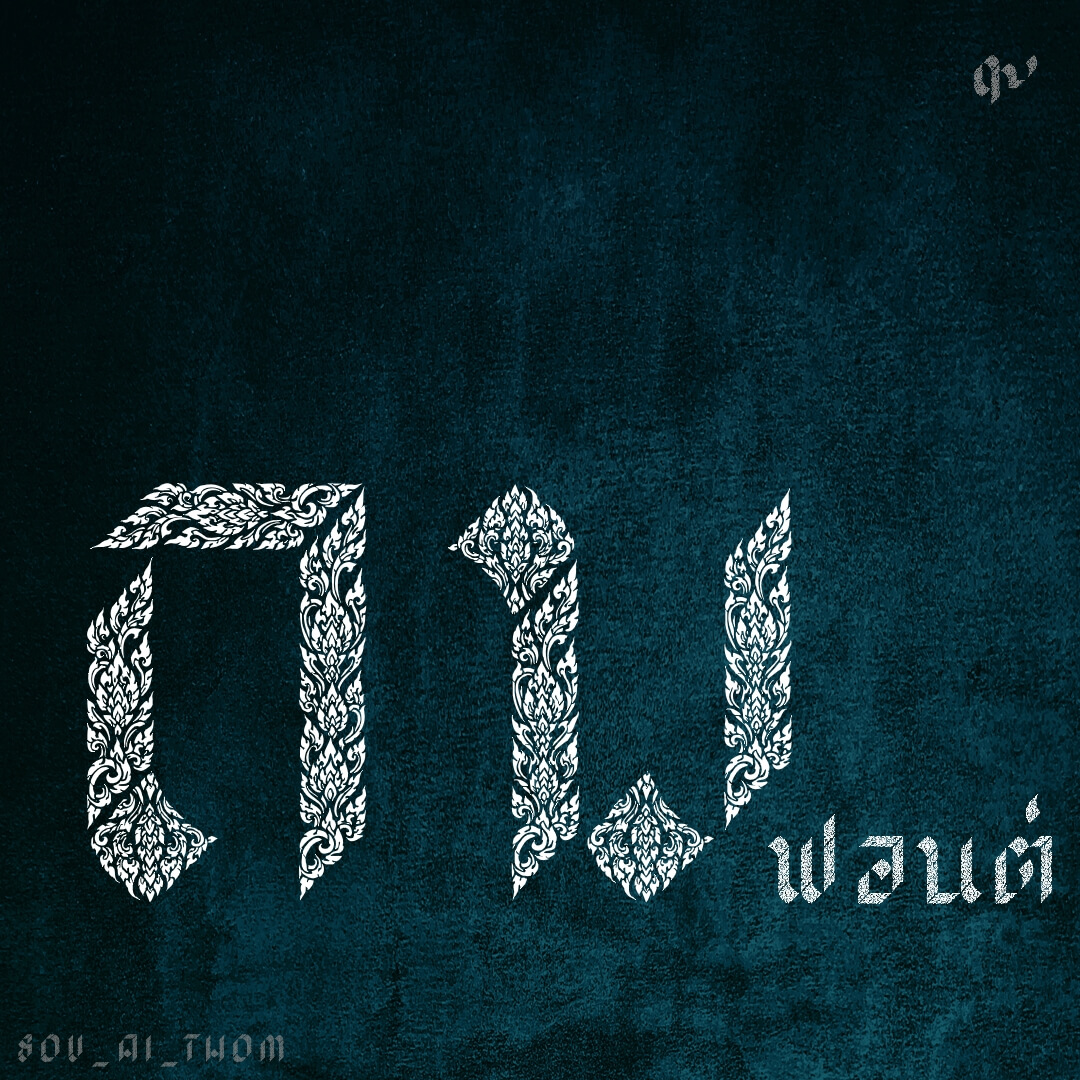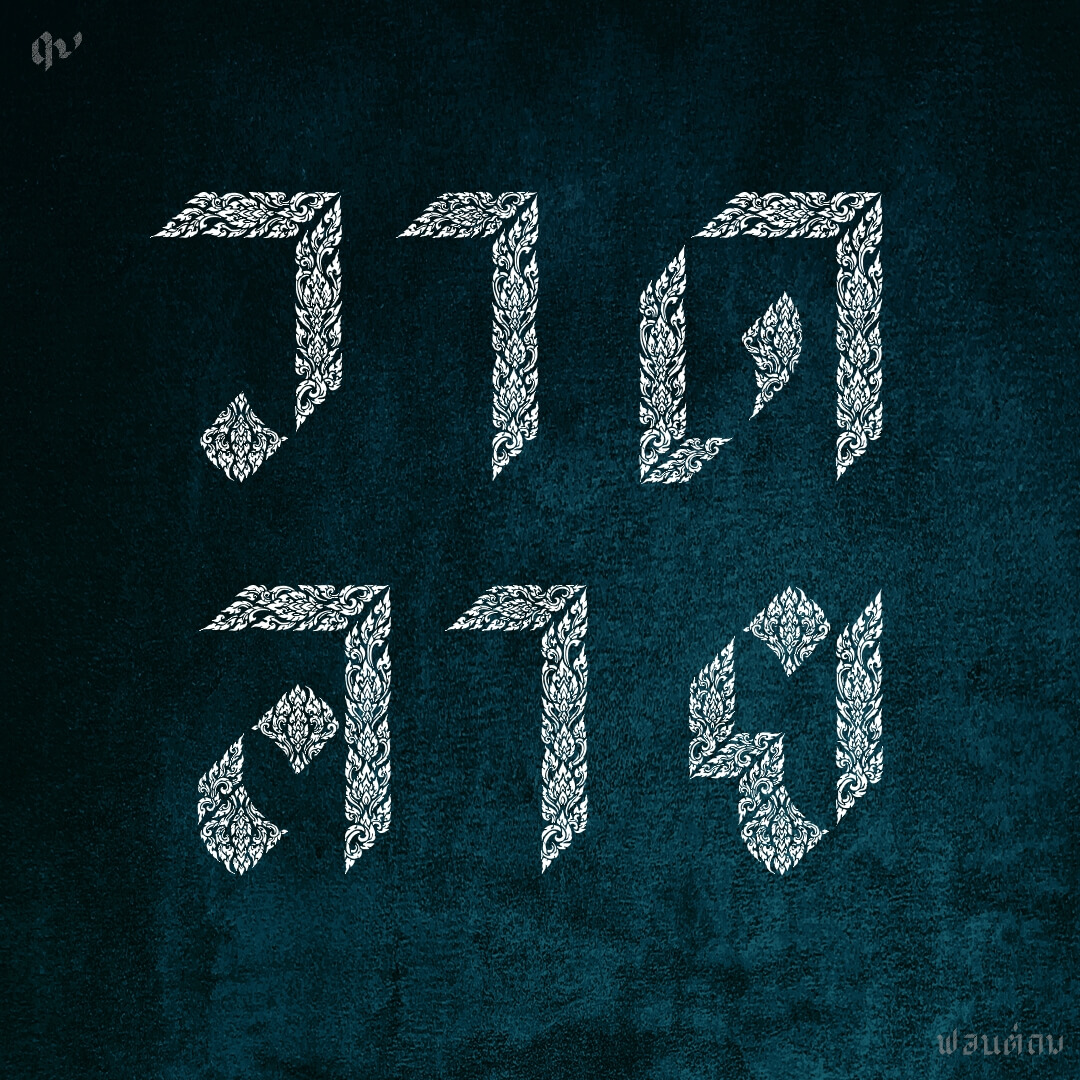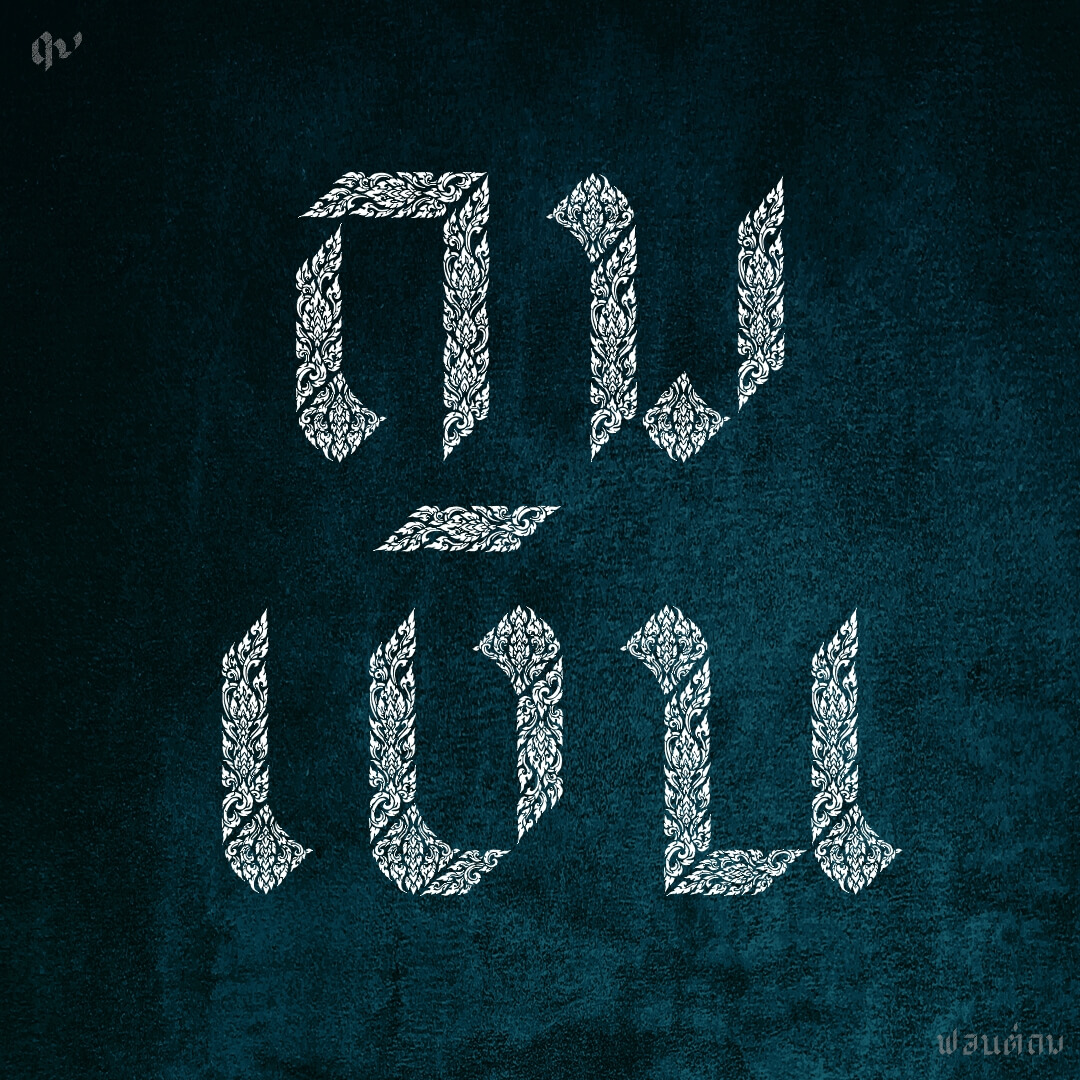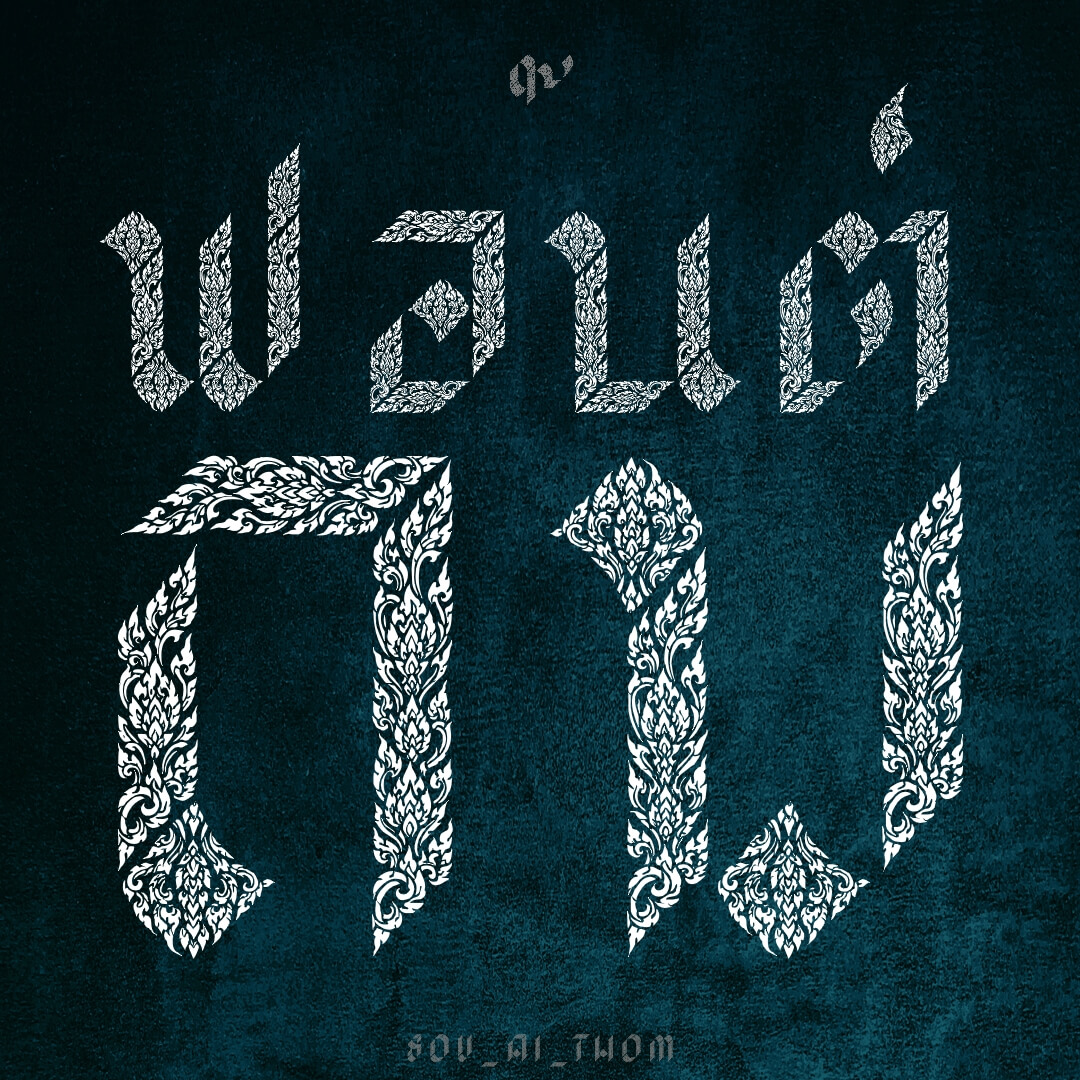
ถม – ชื่อฟอนต์ถม มาจากเครื่องถม ที่มีลายละเอียดเยอะบนพื้นผิว …ทดลองทำฟอนต์ที่มีรายละเอียดยุบยิบ โดยให้ AI gen ลาย บนชื้นส่วนที่เตรียมไว้ 8 ชิ้น แล้วนำมาประกอบเป็นตัวอักษรตามแนวทางฟอนต์นริศอีกที
เบื้องหลังการออกแบบ : ฟอนต์ ถม
ถม (SOV_AI_Thom)